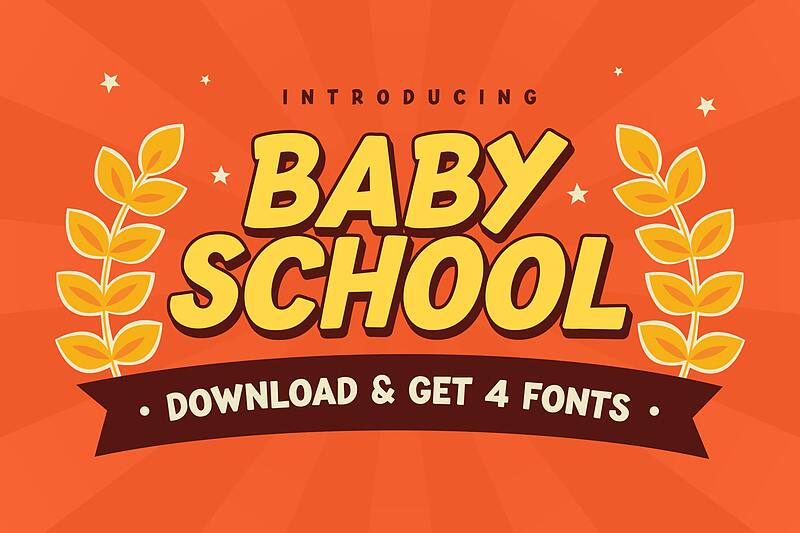
آیا به دنبال یک فونت عالی برای برندسازی، اپلیکیشنهای موبایل، تراکت، مجله، کارت تبریک، کمیک و غیره هستید؟ فونت بِیبی اسکول «مدرسه کودک» بهترین انتخاب است.
فونت بِیبی اسکول فونت جذاب و نمایشی مخصوص کودکان است که برای عناوین، سرخطها، سابتایتلها و موارد دیگر طراحی شده است. این فونت شامل چهار سبک مختلف است و هر حرف آن گوشههای گرد و منحصربهفردی دارد. فونت بِیبی اسکول برای نمایش، عنوان بازیها، متن، چاپ، برندسازی، تابلوها، رابطهای کاربری، دستگاههای تلفن همراه و به ویژه طراحی وب ایدهآل است. این فونت مجموعهای از کاراکترهای بهینه را برای هر طرحی در هر چیدمانی ارائه میدهد.
طبقهبندی: سنس سریف
فاصلهگذاری: نرمال
اندازه بهینه: هر اندازهای